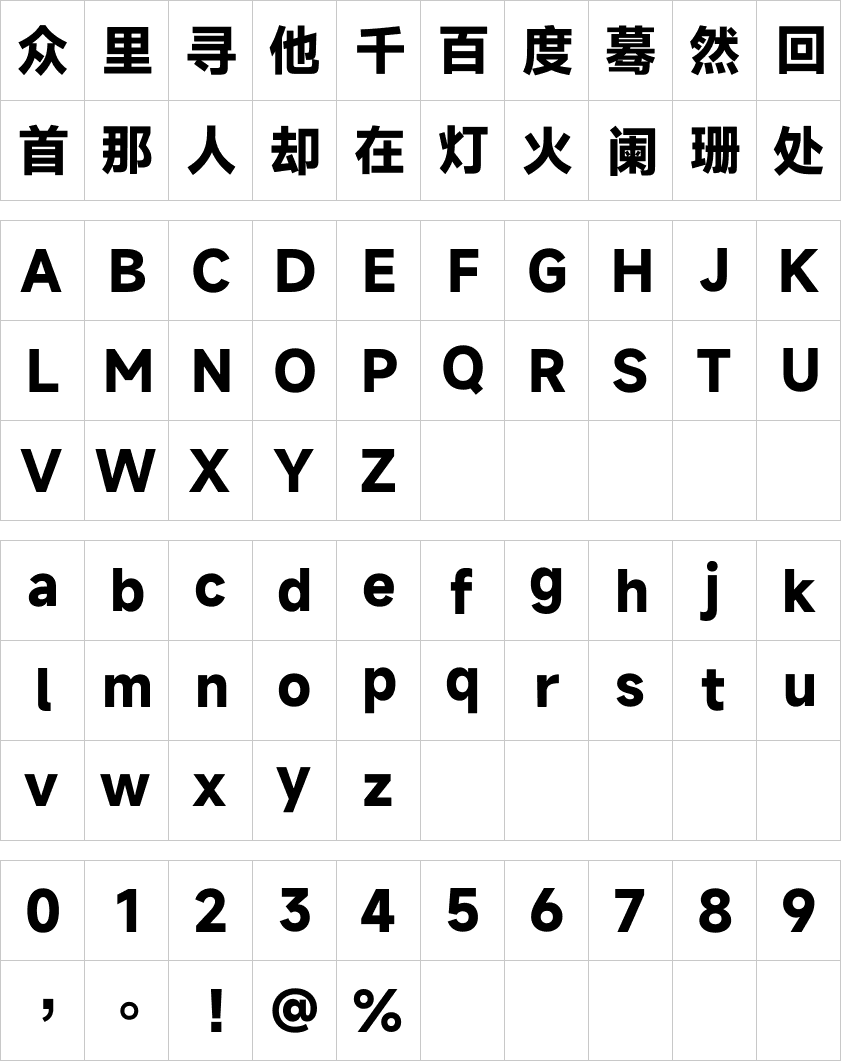
小米MiSans
2021年12月小米推出了小米 12 系列产品以及 MIUI 13 等新品,同时还带来了一款全新系统字体 MiSans。MIUI 13 便是采用了这种全新的系统字体 MiSans。
MiSans字体笔型平直有力,设计更加简约,减少视觉负担,更有利于屏幕显示。共包含29,093个字符,支持多种语言。
MiSans 提供了多种 OpenType 功能,可根据特定需求来选择不同形态的字符,例如某些标点符号可以根据周围字母的形态自动调整至合适的位置。